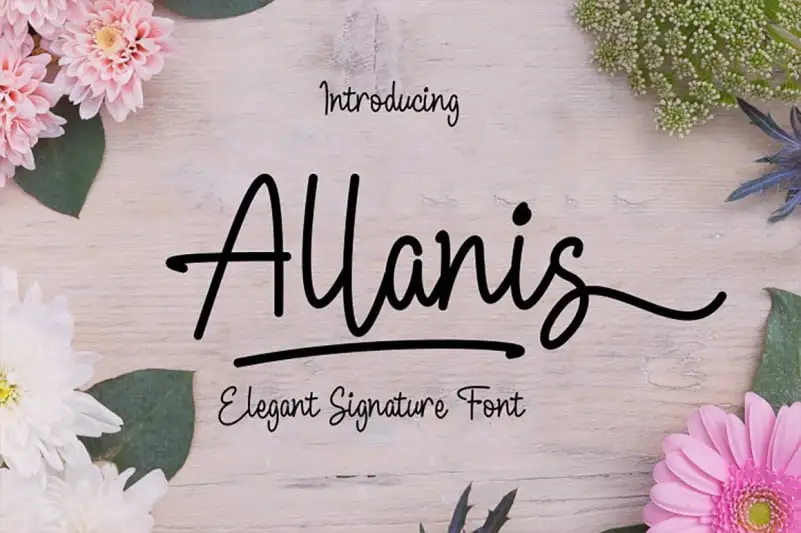
Allanis Handwritten Font – Download Grátis
A fonte ‘Allanis Handwritten Font’ é uma opção perfeita para aqueles que buscam um touch elegante e único em seus projetos digitais. Com seu charmoso estilo à mão escrita, essa fonte oferece uma sensação leve e sofisticada, fazendo-a ser uma escolha ideal para adicionar aquela pitada especial a qualquer projeto de design gráfico. Perfeita tanto para aplicativos móveis quanto para criações web, ‘Allanis Handwritten Font’ se torna uma fonte versátil que pode ajudar você a destacar em um ambiente digital. Seja para o texto do topo da página ou para o subtítulo do seu site, essa fonte será uma escolha inteligente que irá adicionar uma nota de beleza inconfundível a qualquer design. Com seus traços elegantes e suaves, ‘Allanis Handwritten Font’ é um recurso gráfico perfeito tanto para designers profissionais quanto para aqueles iniciantes no campo. Esta fonte não apenas adicionará um toque especial aos seu projetos digitais, mas também pode dar uma sensação de personalidade única a qualquer projeto que você estiver criando. Nesta categoria de fontes à mão escrita, ‘Allanis Handwritten Font’ se destaca por sua leveza e elegância. Para designers em busca de um recurso gráfico moderno e inovador, essa fonte é uma ótima escolha para enriquecer seu trabalho.